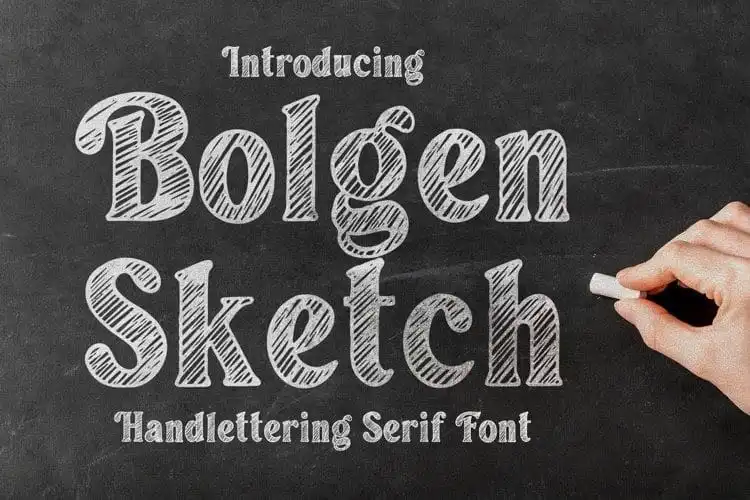
A Bolgen Display Font é uma nova criação do Blankids Studio, apresentada no gênero de fonts displays. Ela traz a personalidade charmosa e versátil dos desenhos livres para fazer seus logotipos ainda mais interessantes e atraentes. Este font tem um tema divertido que se destaca especialmente como recurso para exibição em grandes formatos, criação de camisetas, arte das próprias mãos, adesivos de citações ou até mesmo o design de logotipos. Ideal tanto para designers digitais quanto para aqueles que amam customizar itens manuais com um toque único, a Bolgen Display font oferece uma maneira divertida e criativa de personalizar suas criações.